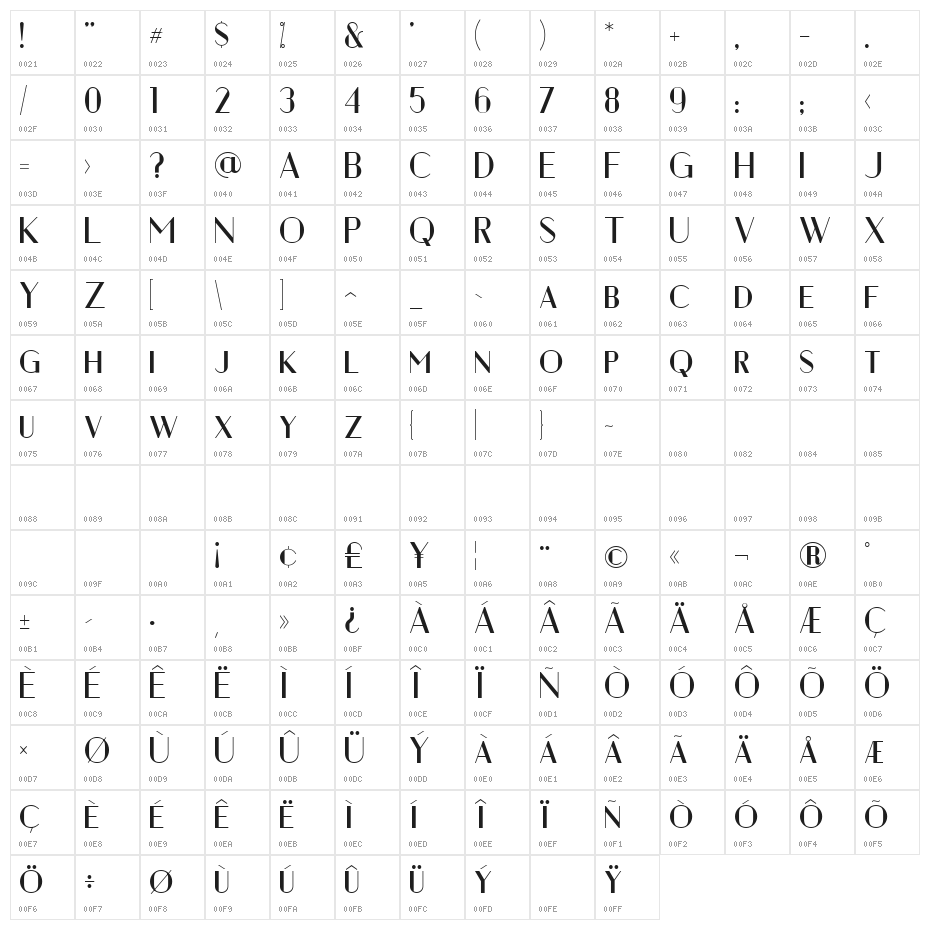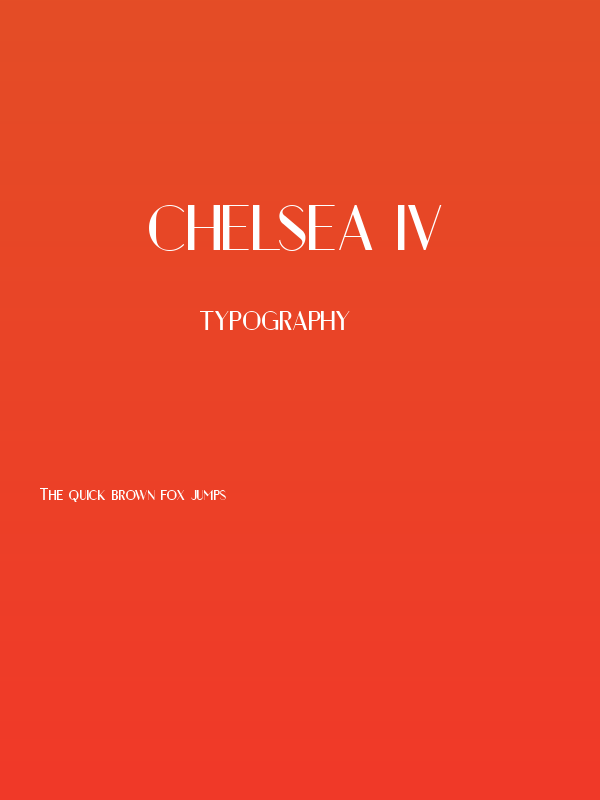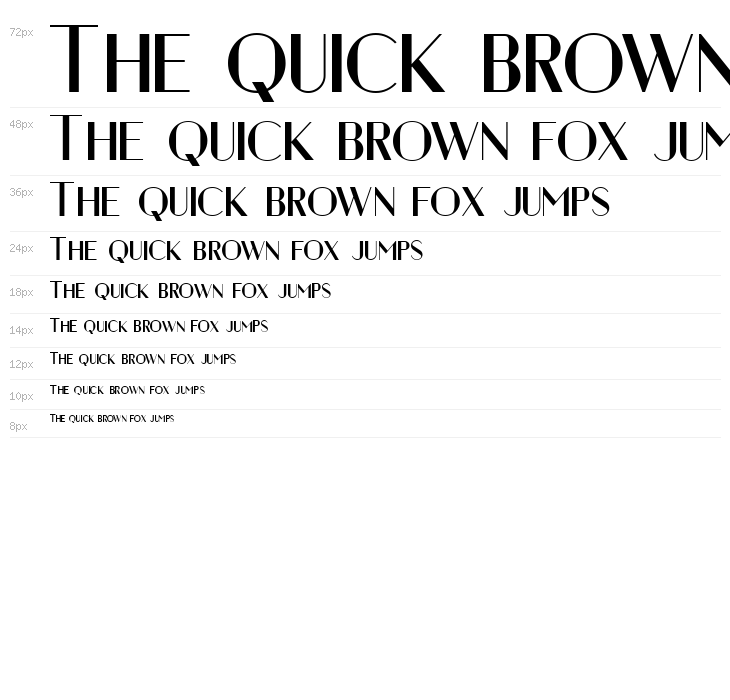
Chelsea IV Font
| Kategorien | Thick |
| Anwendungsfall | Headlines, Logos, Editorial design |
| Vorgeschlagene Projekte | Ideal for luxury branding, editorial design, fashion magazines, and high-end product packaging. |